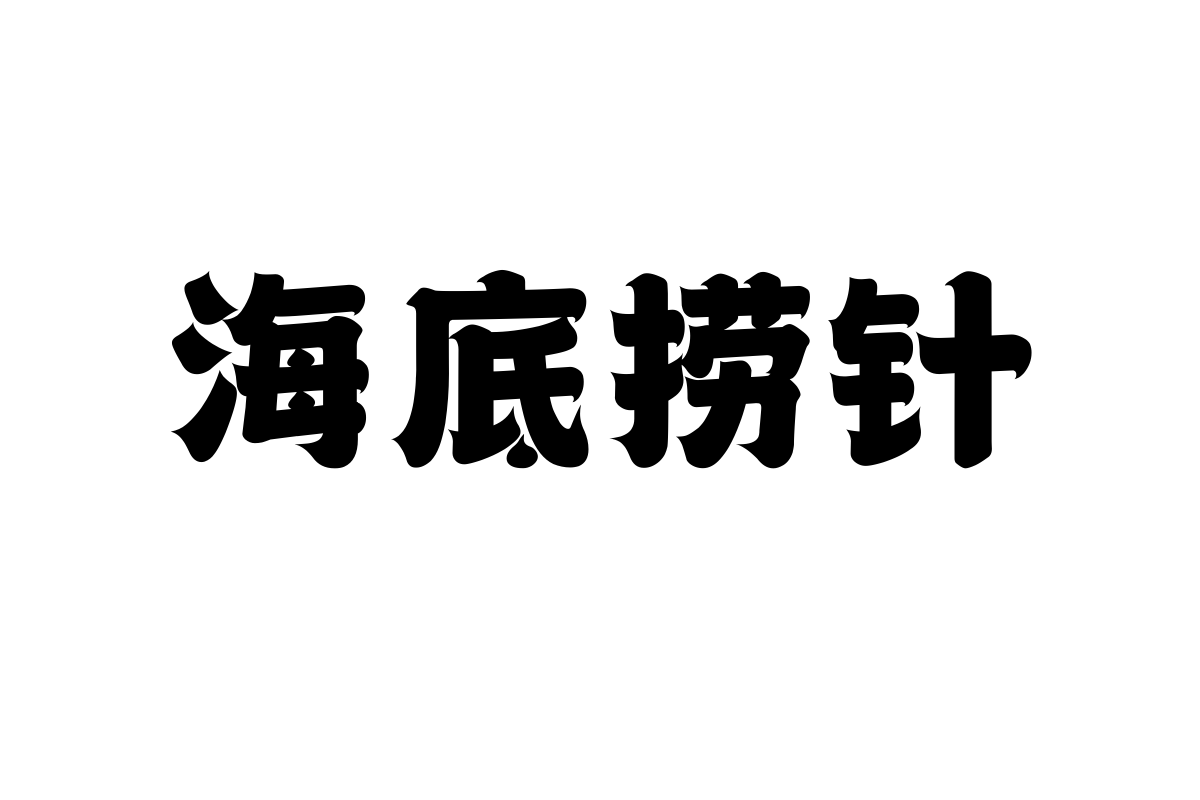
上首虎啸体是一种书法字体,由上首虎啸体书法艺术工作室创作。它的特点是笔画粗壮有力,结构紧凑,线条流畅,给人一种雄壮、豪放的感觉。这种字体适合用于商业广告、宣传海报等场合,能够很好地传达出产品的特点和优势。上首虎啸体在设计中常常被用来表现一种力量感和动感,非常适合用于体育、汽车、游戏等主题的视觉设计。